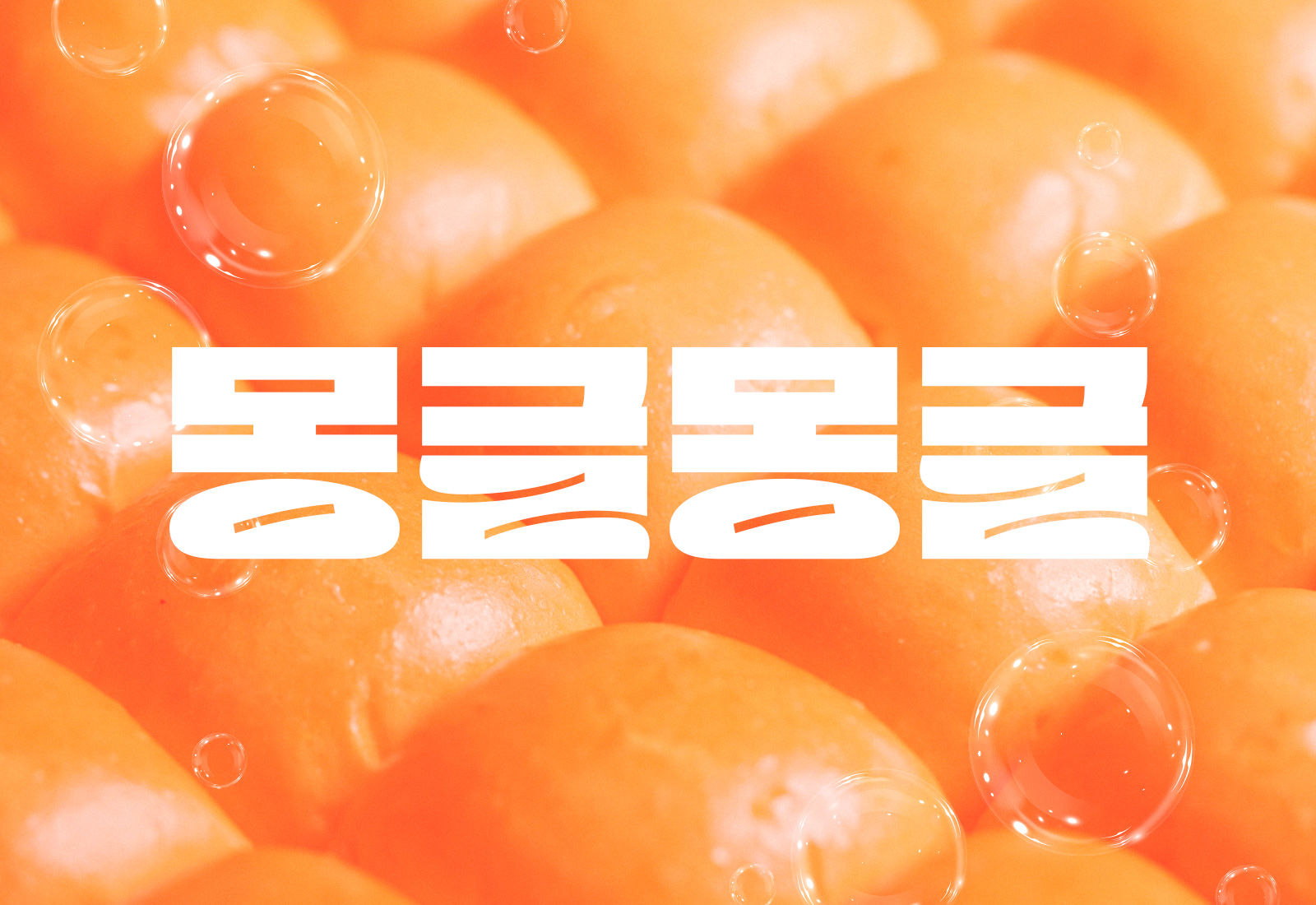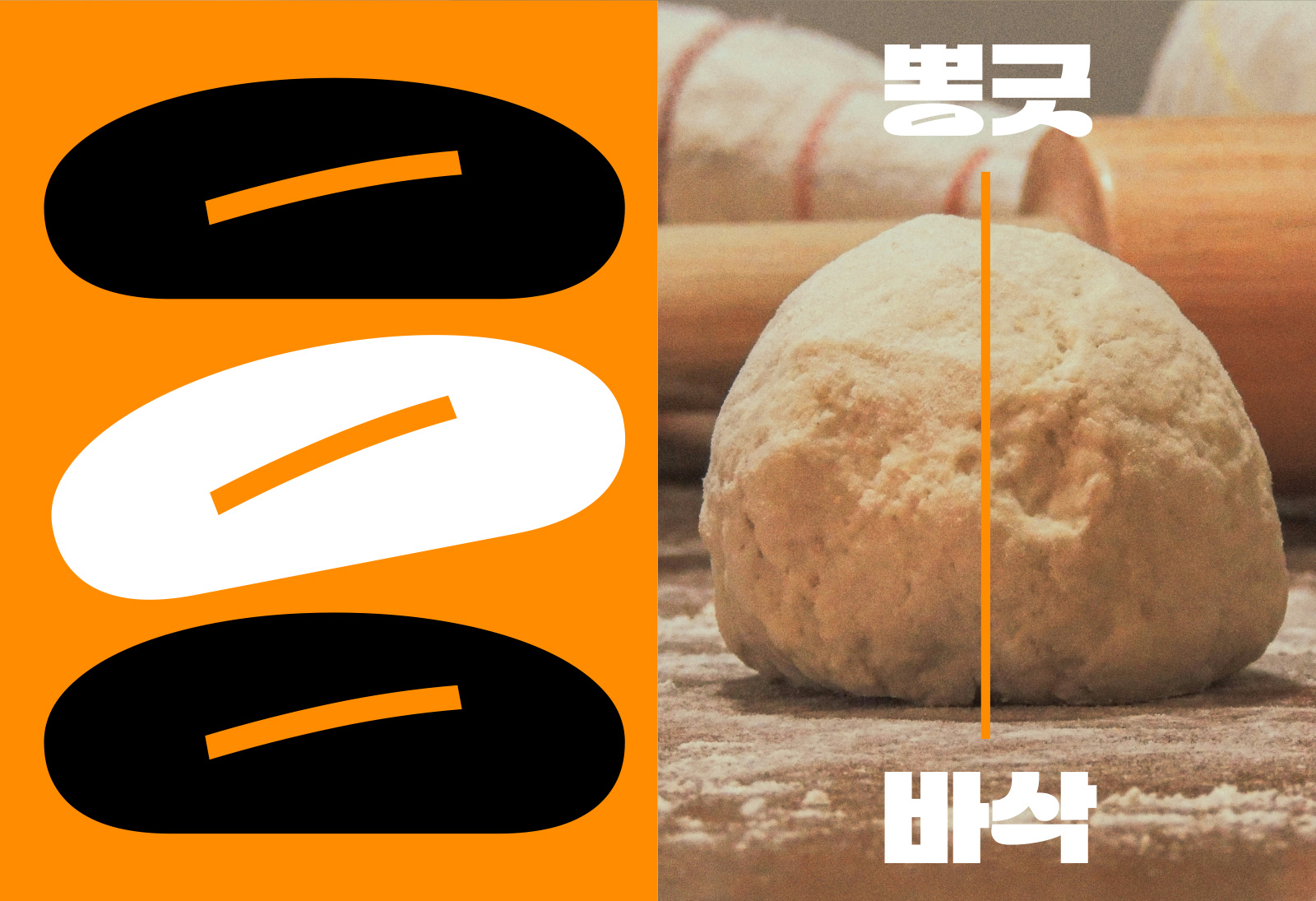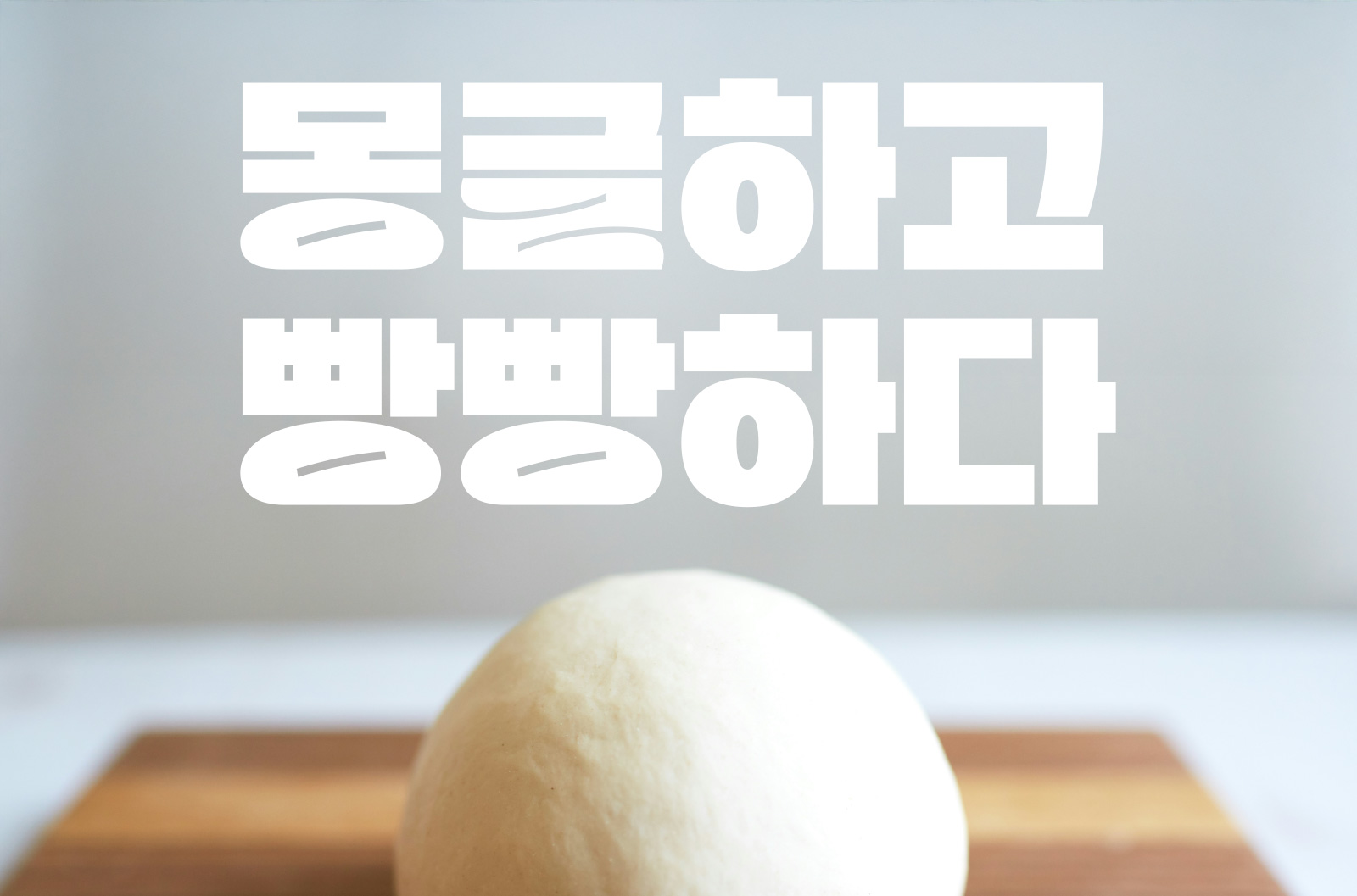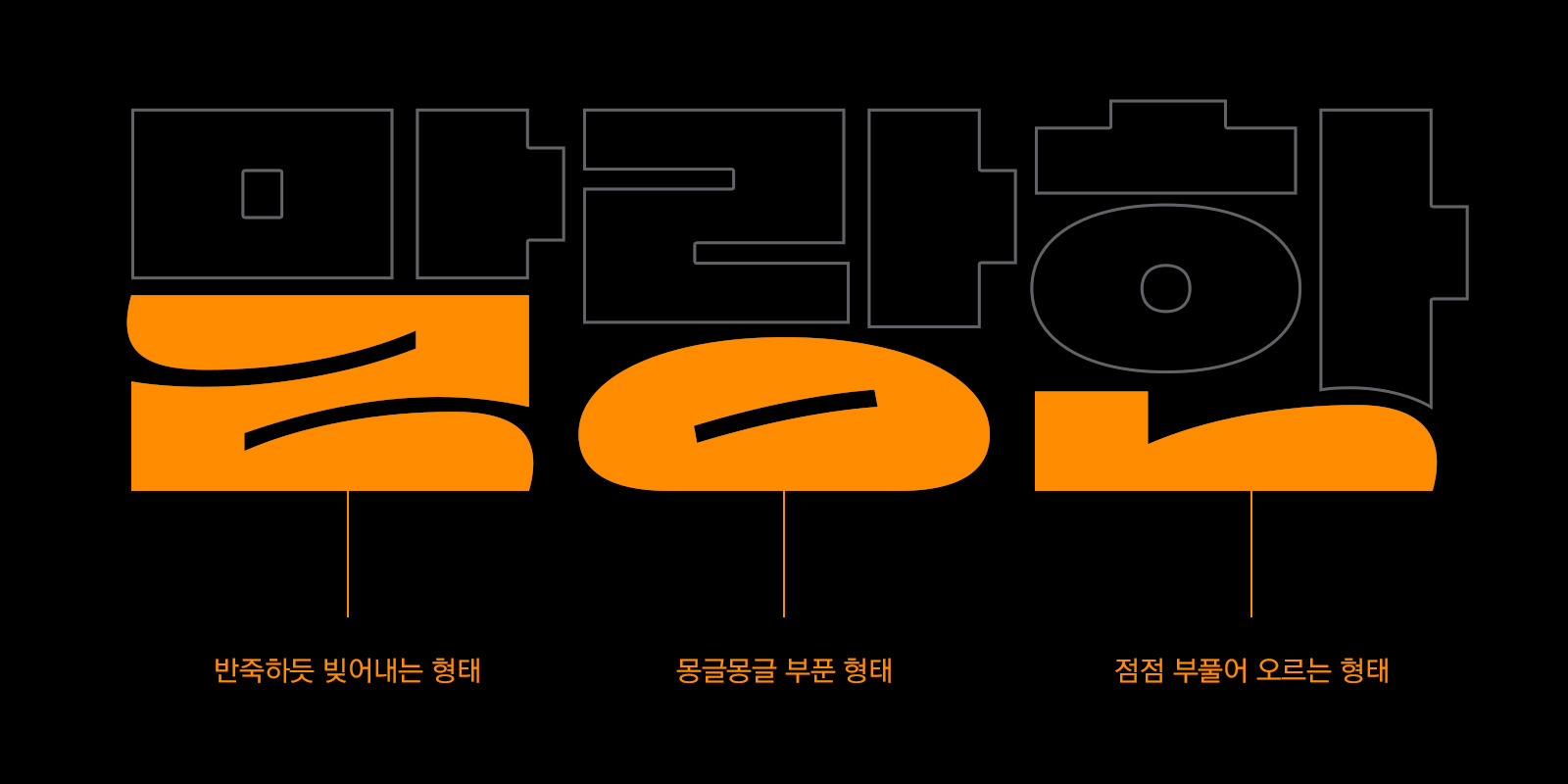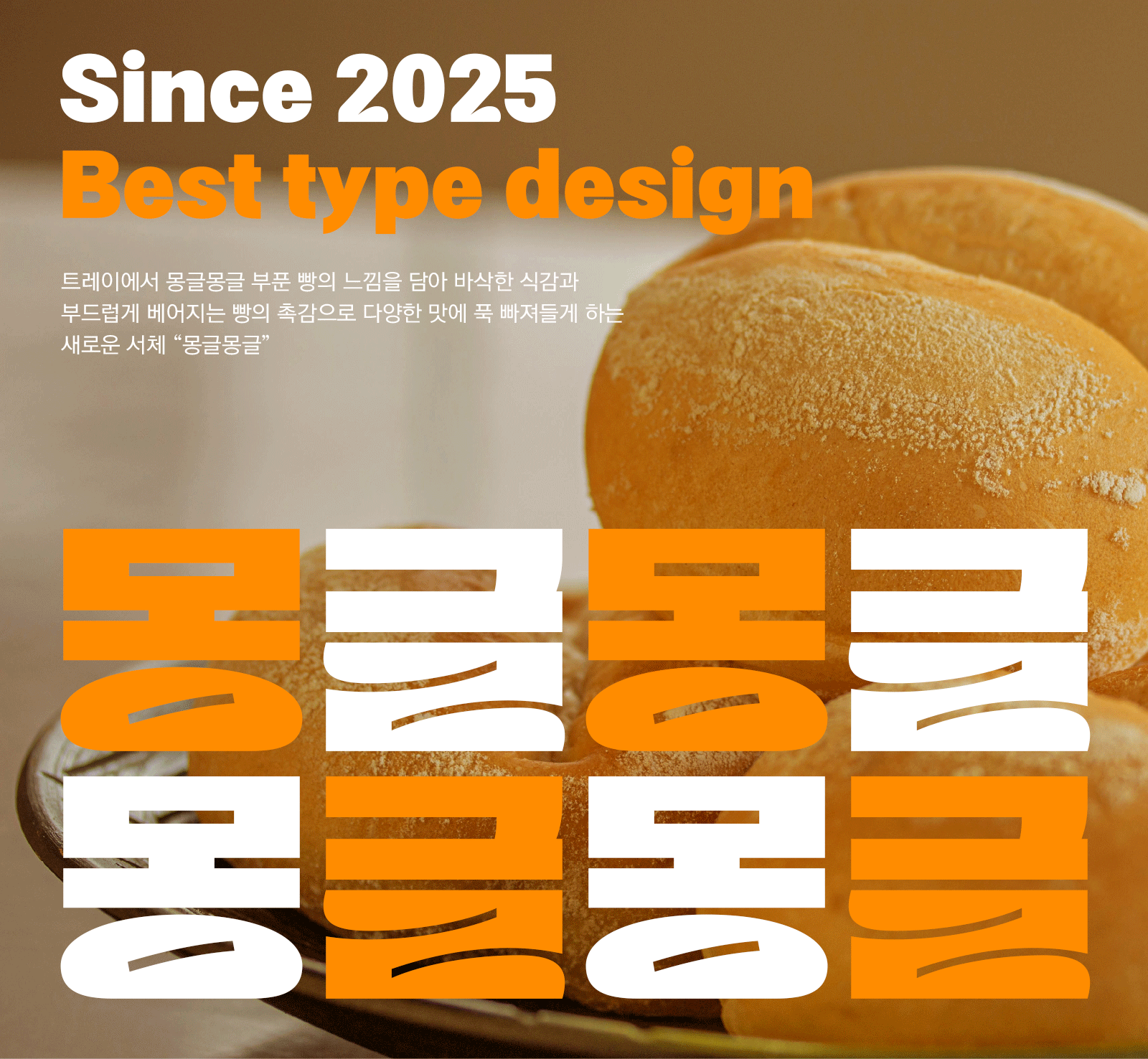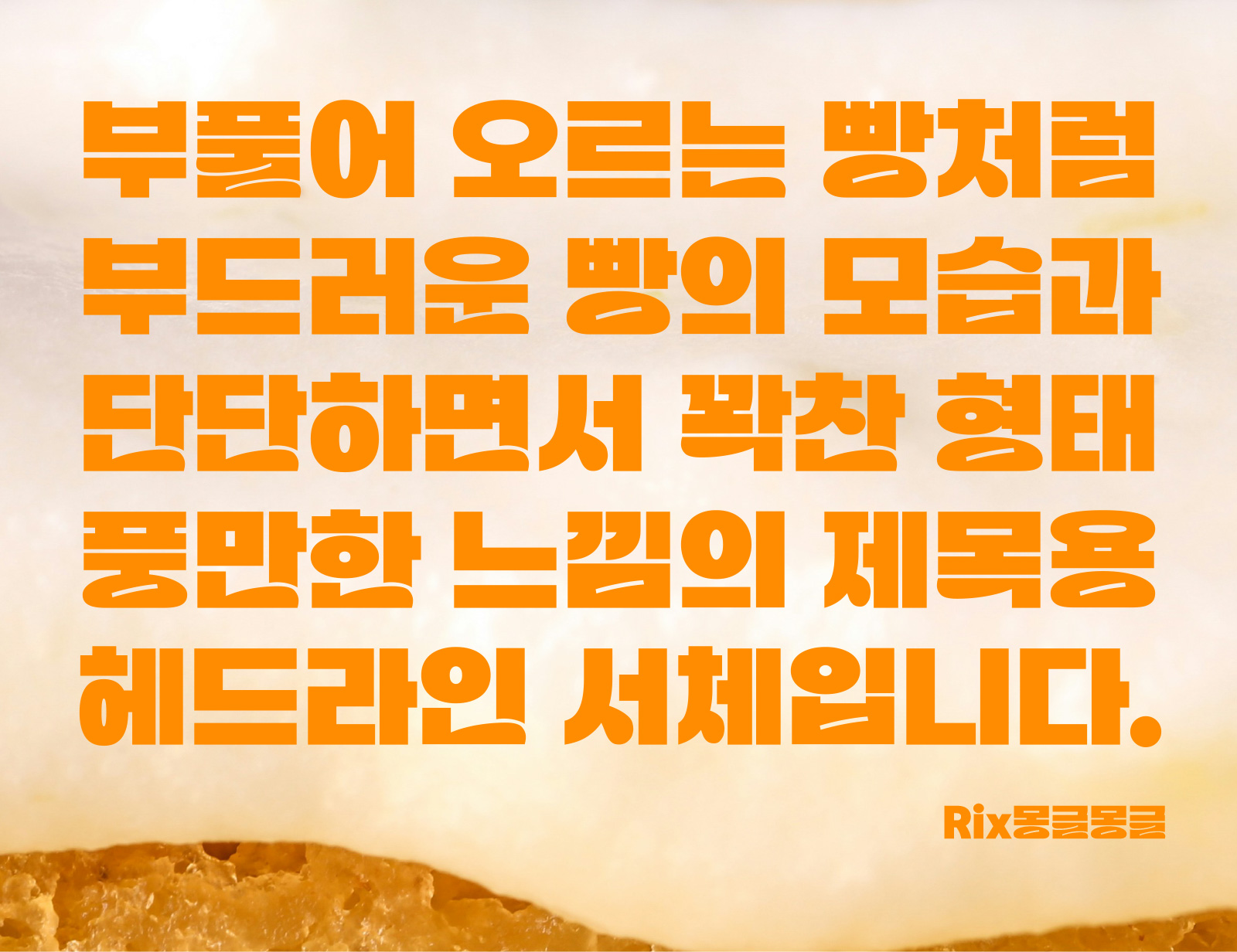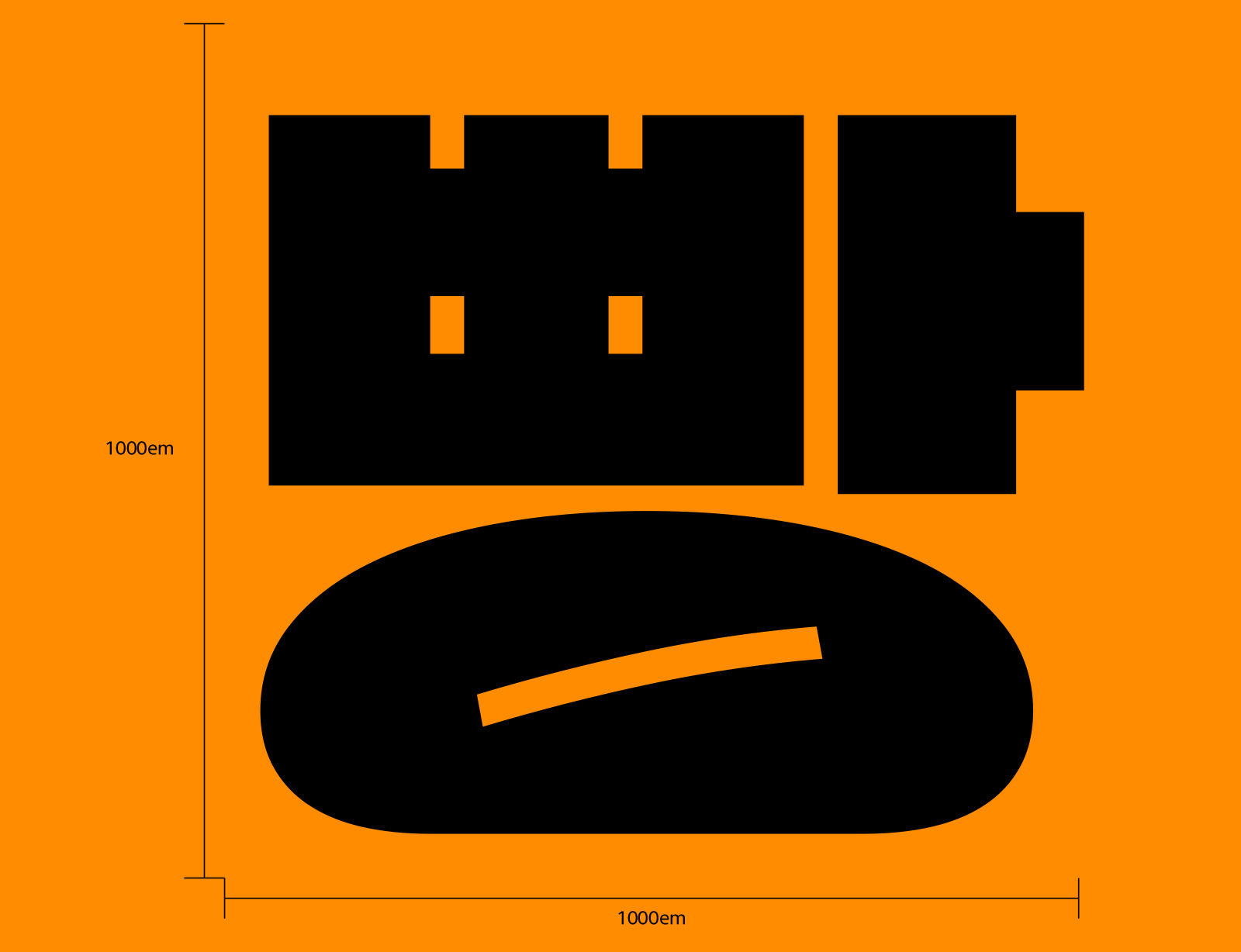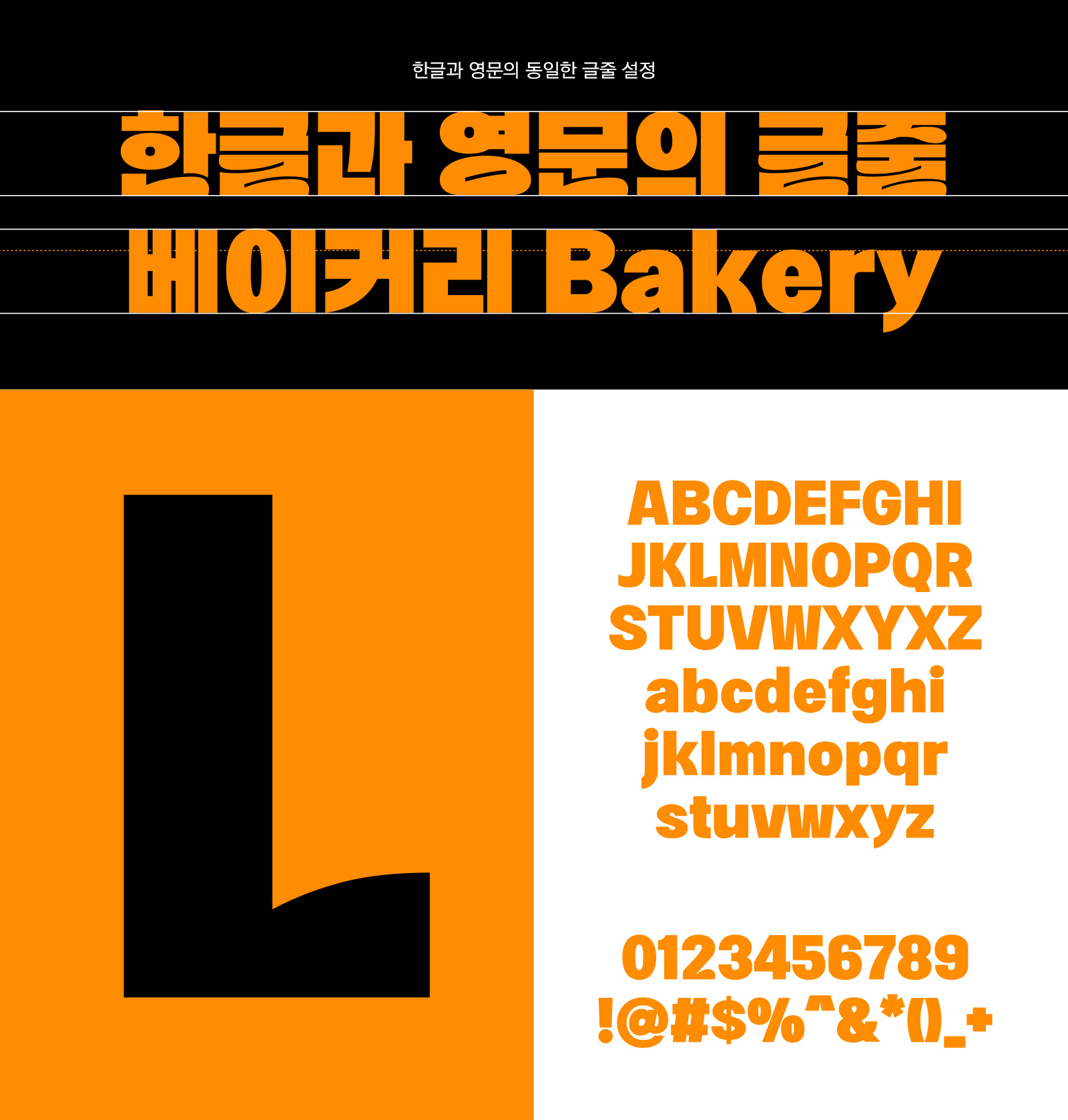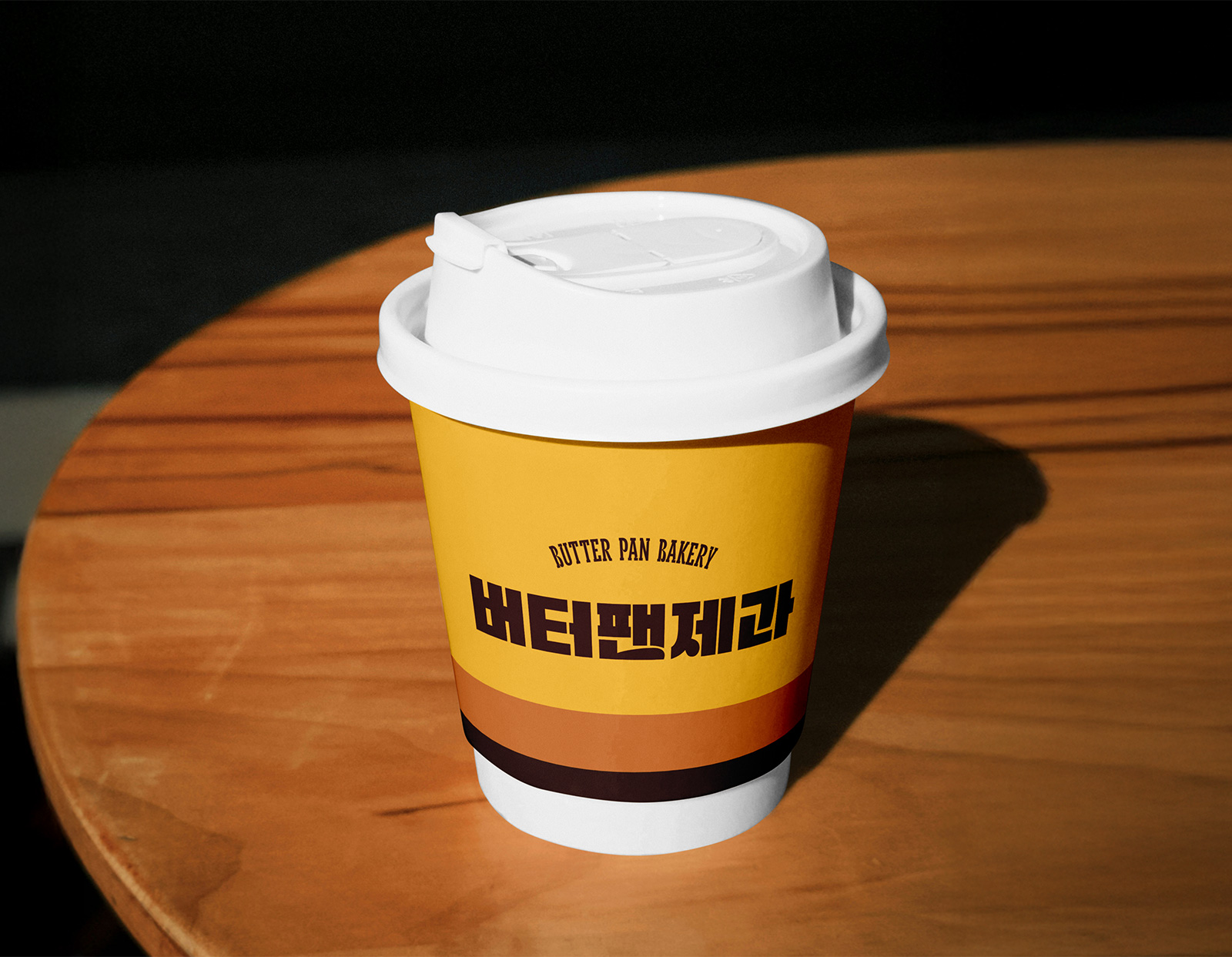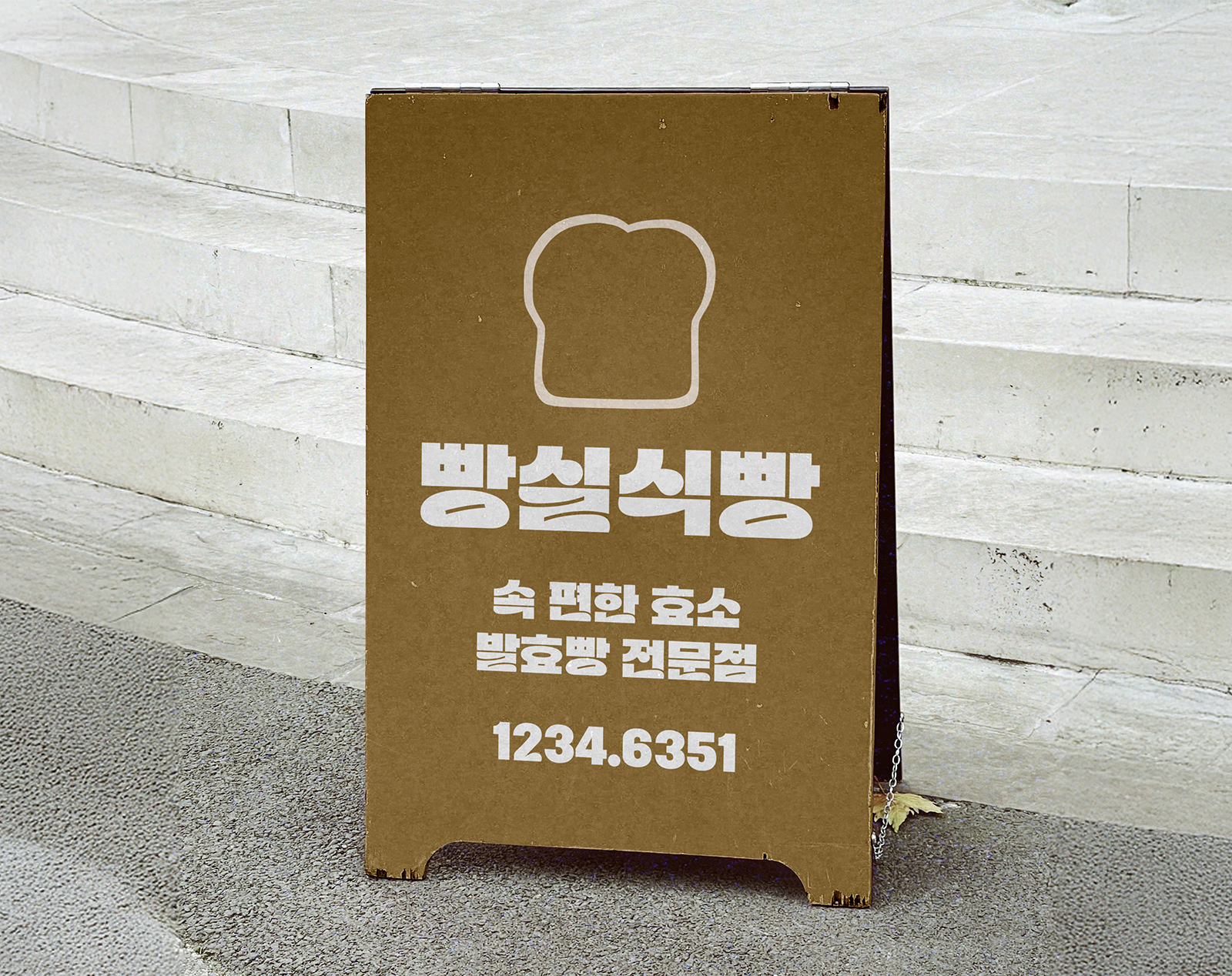
차가운 공기 사이로 몽글몽글한 분위기가 느껴지는 연말입니다. 오늘은 이 분위기와 꼭 맞는 서체 이야기를 들려드리려고 합니다.
김정진 폰트 디자이너의 손끝에서 포근하게 빚어진「 Rix몽글몽글 」, 이 서체가 어떻게 만들어졌는지 함께 알아볼까요?😉
자기소개 부탁드립니다.
안녕하세요. 다양한 글자를 그리고, 연구하고 있는 폰트 디자이너 김정진입니다.
글자가 전달하는 메시지를 시각적 이미지로 그리는 일을 하고 있습니다.
'Rix몽글몽글'은 어떤 배경에서 시작된 서체인가요?
'Rix몽글몽글'은 제목이나 헤드라인에 사용할 수 있으면서도, 단순히 굵기만 강조한 서체가 아닌 확실한 인상과 콘셉트를 가진 그래픽 서체를 만들어보고 싶다는 고민에서 출발했습니다.
기존의 헤드라인 서체들은 다양한 콘텐츠에 무난하게 쓰일 수 있다는 장점은 있지만, 특정 콘셉트나 분위기를 분명하게 드러내야 하는 상황에서는 선택지가 많지 않다고 느꼈어요. 그래서 조금 더 캐릭터가 살아 있고, 시각적으로 기억에 남는 제목용 서체가 필요하다고 생각했습니다.
또 하나의 출발점은, 보통 서체가 하나의 방향성만을 가지는 경우가 많다는 점이었어요. 딱딱하면 딱딱한 느낌으로, 부드러우면 부드러운 느낌으로만 설계되는 경우가 대부분이죠. 이번 작업에서는 그런 단일한 콘셉트에서 벗어나, 서로 다른 두 가지 매력, 단단함과 몽글몽글한 부드러움이 공존하는 글자를 만들어보고 싶었습니다.
그렇게 서로 상반된 인상이 자연스럽게 어우러지는 제목용 서체를 목표로 하면서, 'Rix몽글몽글'이 만들어지게 되었습니다.
서체에서 빵의 쫀듯하고 말랑한 질감이 느껴지는데 눈길을 사로잡는 이 콘셉트는 어떻게 만들어졌나요?
'Rix몽글몽글'은 부풀어 오르는 빵처럼 부드러운 질감과 단단하면서도 풍만한 인상을 동시에 담아낸 제목용 서체입니다. 강하고 단단한 인상을 기본으로 하되, 그 안에 부드러운 포인트를 더해 빵이 서서히 부풀어 오르는 순간을 서체의 형태로 표현하고자 했어요.
획의 구조나 전체적인 실루엣에서는 힘 있는 인상을 유지하면서도, 곡선 처리와 받침의 형태를 통해 말랑한 느낌이 자연스럽게 드러나도록 설계했습니다. 이런 상반된 요소들이 조화를 이루며 서체만의 개성이 만들어졌다고 생각해요.
서체 이름인 '몽글몽글' 역시, 너무 단단한 이미지보다는 부드러운 포인트에서 느껴지는 인상을 직관적으로 전하고 싶어 선택하게 되었습니다.
'Rix몽글몽글'만의 가장 큰 특징이나 차별점은 무엇인가요?
'Rix몽글몽글'의 가장 큰 특징은 단단한 구조감과 몽글한 감성이 한 글자 안에서 동시에 드러난다는 점입니다. 초성에는 힘 있는 형태감을 적용해 제목용 서체에 필요한 구조적 안정감을 확보했고, 종성에는 부드러운 곡선을 더해 말랑하게 부풀어 오르는 인상을 표현했습니다.
특히 빵 반죽에서 착안한 디자인 아이디어를 바탕으로, 사용 빈도가 높은 'ㄹ, ㅇ, ㄴ' 받침에 개성 있는 조형을 담은 점이 차별화된 요소입니다. 반죽을 비비듯 이어지는 형태의 ‘ㄹ’, 살짝 부풀어 오른 반죽을 형상화한 ‘ㅇ’, 오븐에서 팽창하는 모습을 모티브로 한 ‘ㄴ’ 등은 서체의 콘셉트를 가장 직관적으로 보여주는 글자들이에요.
이처럼 글자의 기본 골격은 견고하게 유지하면서도, 세부적인 형태에서는 부드러운 볼륨과 리듬감을 더해 강한 존재감과 말랑한 인상이 동시에 느껴지는 제목용 서체로 완성한 것이 'Rix몽글몽글'만의 특징이라고 생각합니다.
'Rix몽글몽글'은 어떤 콘텐츠나 작업에서 특히 효과적으로 활용할 수 있을까요? 디자이너로서 추천하고 싶은 활용 포인트도 함께 들려주세요.
'Rix몽글몽글'은 제목용 헤드라인 서체로, 강한 시각적 인상을 전달해야 하는 콘텐츠에 특히 잘 어울립니다. 글자 자체가 가진 구조감과 볼륨감이 분명해 포스터, 옥외광고, 영상 타이틀이나 자막처럼 시선을 빠르게 사로잡아야 하는 작업에서 효과적으로 사용할 수 있어요.
또한 독특한 그래픽 인상을 지닌 서체이기 때문에, 단순한 텍스트를 넘어 이미지처럼 활용하는 디자인 작업에도 적합합니다. 패키지 디자인이나 SNS 타이틀, 브랜드 키비주얼처럼 콘셉트 전달이 중요한 콘텐츠에서도 서체 하나만으로 충분한 포인트가 될 수 있다고 생각해요.
강한 존재감과 부드러운 인상이 함께 느껴지는 서체인 만큼, 개성이 필요한 장면에서 부담 없이 사용할 수 있다는 점이 'Rix몽글몽글'의 활용 포인트입니다.
제작 과정에서 특히 고민이 많았던 부분이나 기억에 남는 시행착오가 있다면 들려주세요.
보통 한글 서체를 제작할 때는 특정 자소에 특징을 주면, 다른 자소들도 그 아이덴티티를 자연스럽게 따라가도록 설계하는 경우가 많습니다. 예를 들어 받침 'ㅇ'에 특징을 주었다면, 초성 'ㅇ' 역시 같은 성격을 유지하는 방식이 일반적이죠.
하지만 'Rix몽글몽글'은 그런 관습에서 벗어난 접근을 시도했습니다. 초성에는 단단한 인상을 주기 위해 비교적 딱딱한 형태를 적용하고, 반대로 받침에서는 부드러움을 강조하기 위해 곡선 위주의 형태를 설계했어요. 이처럼 자소의 역할에 따라 성격을 다르게 가져가는 방식이 쉽지는 않았지만, 결과적으로 서체의 콘셉트를 가장 잘 드러내는 지점이 되었다고 생각합니다.
서체 작업을 마친 소감이 궁금합니다.
하나의 폰트 안에 서로 상반되는 두 이미지를 담는 시도는 개인적으로도 새로운 도전이었습니다. 단단함과 부드러움이라는 서로 다른 인상을 하나의 글자로 조화롭게 풀어내기 위해 많은 실험과 고민이 필요했어요. 그 과정이 쉽지만은 않았지만,
결과적으로 지금의 'Rix몽글몽글'이라는 서체로 완성될 수 있어 무척 뿌듯하게 생각하고 있습니다.
이 서체를 사용하는 분들께 전하고 싶은 메시지가 있다면요?
'Rix몽글몽글'은 단일한 이미지에 집중된 서체라기보다는, 두 가지 매력이 자연스럽게 조화를 이루는 서체입니다. 강한 인상을 전달하면서도 동시에 부드러운 감성을 담고 있기 때문에, 분명한 인상을 가진 서체이면서도 다양한 시각 산출물과 작업에서 유연하게 활용할 수 있을 거라 생각해요.
상황에 따라 다른 표정을 보여줄 수 있는 서체인 만큼, 여러 디자인 작업에서 자유롭게 활용해보시길 바랍니다.
추가로 전하고 싶은 이야기가 있다면 자유롭게 들려주세요.
한글 서체 디자인은 이미 많은 결과물이 나와 있어서 더 이상 새로울 게 없다고 느껴질 때도 있습니다. 하지만 조금만 시선을 바꿔 보면, 여전히 다양한 접근 방식과 새로운 디자인 가능성이 많이 남아 있다고 생각해요.
폰트릭스는 앞으로도 이런 상상력을 바탕으로, 우리가 아직 경험하지 못한 다양한 이미지의 서체들을 꾸준히 준비해 선보이고자 합니다.
그런 흐름 속에서, 내년에는 서체를 접하는 사람들이 조금이라도 새로운 이미지를 경험하고 그 안에서 자연스럽게 디자인 영감을 얻을 수 있으면 좋겠다고 생각해요. 하나의 유형을 따르기보다는, 다양한 스타일을 제안하는 방식으로 작업을 이어가고 싶습니다.
그리고 개인적으로는, 올겨울 독감으로 꽤 고생을 했던 기억이 남아 있어서요.
내년의 자신에게는 무엇보다 아프지 말고, 건강하게 작업을 이어가자는 말을 꼭 전하고 싶습니다.
몽글하고 빵빵하게 말랑한 제목용 감성 🍞
빵 반죽에서 영감을 얻은 'ㅇ'의 몽글한 볼륨과 'ㄹ'의 말랑한 흐름이 어우러져 글자 자체로도 부드럽고 유쾌한 리듬을 만듭니다.
개별 글자의 개성을 살리면서도 여러 글자가 어우러질 때 안정적인 리듬과 균형감을 만들어냅니다.
네모 틀 안에서 가득 찬 구조에 몽글한 볼륨을 더해 몽글빵빵한 매력이 공존하는 인상을 완성했습니다.
한글과 영문, 숫자를 동일한 글줄 기준으로 설계해 다양한 조합에서도 깔끔한 정렬감을 보여줍니다.
갓 만든 빵에서 은은하게 퍼지는 고소함처럼, 'Rix몽글몽글'은 글자 안에 말랑한 여운을 남깁니다. 🍞
일상적인 문장 속에 재미난 리듬과 몽글한 인상을 더하고 싶다면, 서로 다른 두 매력이 하나의 글자에 공존하는 'Rix몽글몽글'이 제목용 서체의 새로운 선택지가 되어줄 것입니다. 포근하고 따뜻한 연말 보내세요🎅